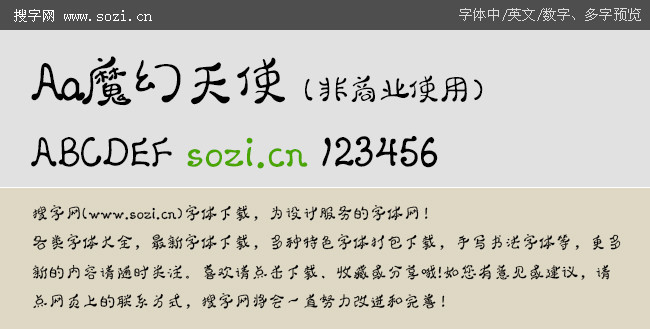
Aa魔幻天使
搜字網(wǎng)給大家提供一款Aa魔幻天使(非商業(yè)使用)中文字體下載,該字體是一款卡通風格的藝術字體,字體筆觸粗細適中,字形圓潤可愛,適合應用于藝術設計、平面宣傳設計、網(wǎng)頁設計、海報設計等應用(此字體為個人非商用版,商用可以聯(lián)系QQ:1006760504)。